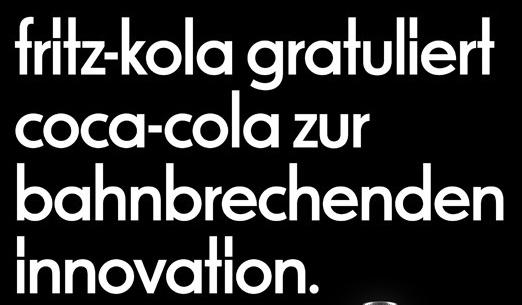
Spezial-Schrift FRITZ-KOLA ?
Nach welchem Vorbild (Futura, Geometrix, ???) haben die Schriftschneider
diese sehr individuelle, aber formschöne, mit betontem Gleichstrich erstellte
Schrift geformt? - - Die Rundungen und Kurven finde ich ganz besonders schön.
Wahrsch. ist die Schrift eine geschützte Type.
mit der Geometrix meinst Du die Neuzeit Grotesk bzw einen derer Klone? Die Vorlage für diese Schrift waren sicherlich die geometrisch konstruierten Grotesk aus dem Deutschland der 1920er. Aber das ist noch Pre-Futura, denn diese ist schwer humanistisch angehaucht, hat also stärkere Strichdickenkontraste und auch andere Anschnitte bei einigen Buchstaben (kleines c). Die alte „Bahnhofsfutura“ ist IMHO noch näher dran ... https://www.kai.gs/bahnhofsfutura/